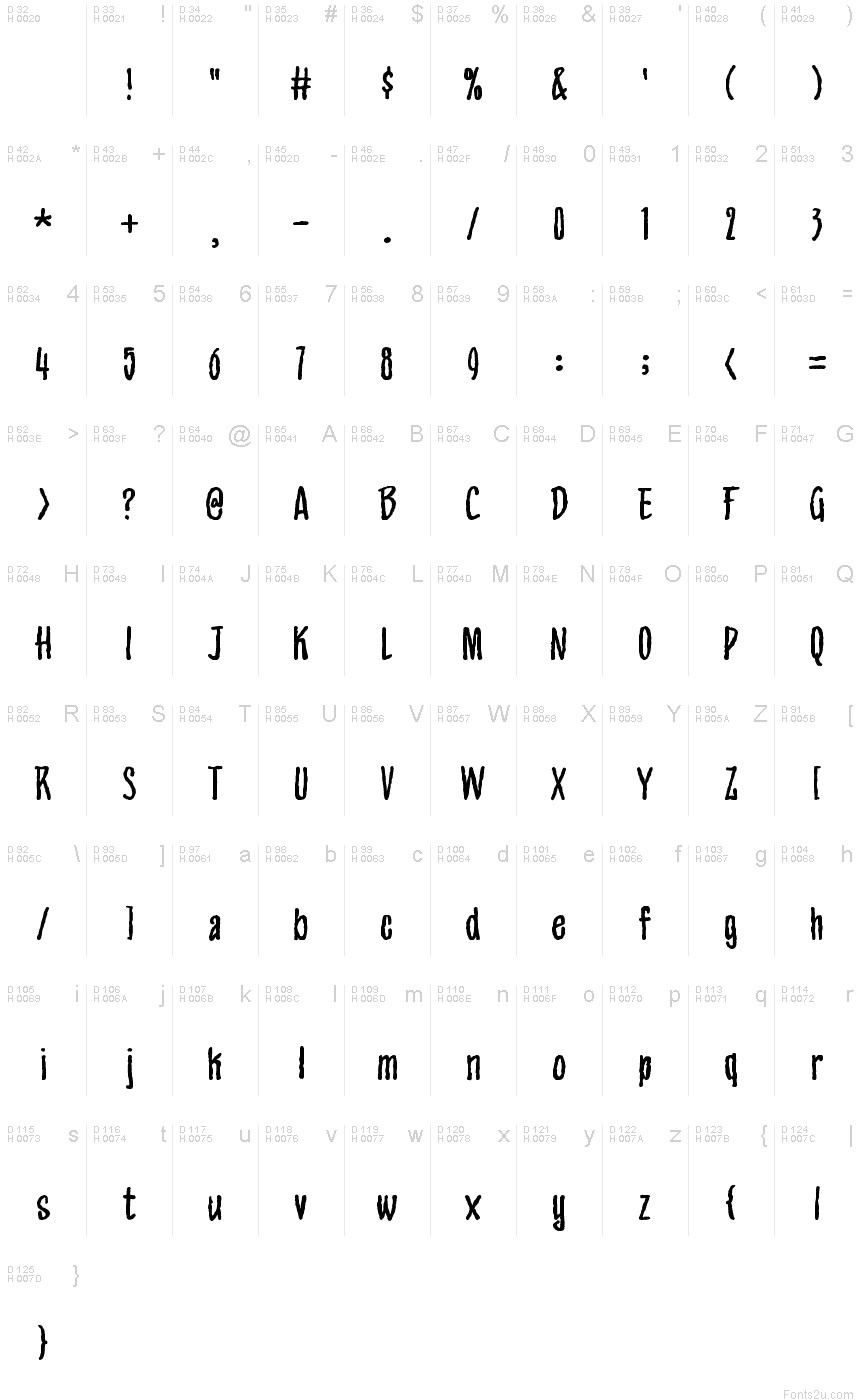
Appetite autorstwa Jakoba Fischera z PizzaDude to darmowy, zniekształcony krój displayowy, który wygląda, jakby został naszkicowany grubym markerem z lekko rozmazanymi krawędziami. Litery są wysokie, wąskie i nieco chwiejne, z kleksami tuszu oraz miękkimi, nieregularnymi konturami, co nadaje każdemu słowu niespokojną, ręcznie stworzoną energię. Całość sprawia wrażenie surowej i nieco psotnej – niczym notatka napisana w pośpiechu na kuchennym blacie.
Stosując Appetite, zyskujesz teksturę, która natychmiast przełamuje cyfrową sterylność, dodając nagłówkom charakteru i pazura. Ten darmowy font świetnie sprawdzi się na plakatach koncertowych, okładkach albumów indie, zinach, opakowaniach przekąsek, tytułach horrorów komediowych czy odważnych grafikach do social mediów. Użyj go w dużym rozmiarze i z luźnym światłem, aby uzyskać maksymalny efekt, a w tekście głównym połącz Appetite z czystym, neutralnym bezszeryfem, dzięki czemu zachowasz czytelność projektów, podczas gdy nagłówki będą szaleć.